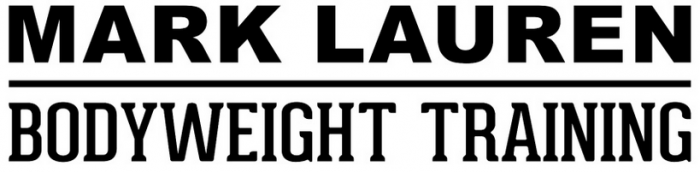
Welche Schrift ist das? Mark Lauren Bodyweight Training
ich bin auf der Suche nach den beiden Schriftarten.
Nun, beim ersten Font kann ich deinen Wunsch erfüllen, denn hast Du Windows, hast du den Font längst, es ist nämliuch schlicht Arial Black.
Es handelt sich hier um Geared Slab Regular von Ben Dalrymple, und ist zusammen mit 3 weiteren Schnittel für gerade einmal $ 10,-- (für die kommerzielle Lizenz für 5 Arbeitsplätze) bei Lost Type zu haben.
da ist zuerst eine Arial in Black.
Die Slabserif habe ich nicht in den Unterlagen ... Die Suchmaschine von Myfonts.com liefert mir die Rama Slab vom Flat-IT ... was aber ein Fehler ist ...Serifen zu lang ... Whatfont ist besser ... Geared Slab ...
Flat-IT taucht langsam auf identifont auf und ich kann die Schriften Stück für Stück katalogisieren. Losttype ist da leider noch etwas hinten drann ...
Und so ist, auch wenn man die Möglichkeit hat, so genannte Coinstallationen auch abzuwählen, jeder dieser Downloadmanager eben heuristisch gesehen eben ein Trojaner.
In etwa so, alas hätten damals vor Troja die Griechen neben das Holzpferd noch einen Mann gestellt, der sich ein Übergabeprotokoll für den von den besten Handwerkern gebauten, hochwertigen und völlig kostenlos übergebenen Kultgegenstand unterschreiben lässt, in dem aber auf Seite 96 von 120 steht, dass mit Übernahme des Kultgegenstandes auch eine völlig kostenfreie Überprüfung der inneren Sicherheitsmaßnahmen Trojas durch die besten griechischen Sicherheits-Fachkräfte stattfinden wird, sofern dies nicht ausdrücklich abgewählt wird.